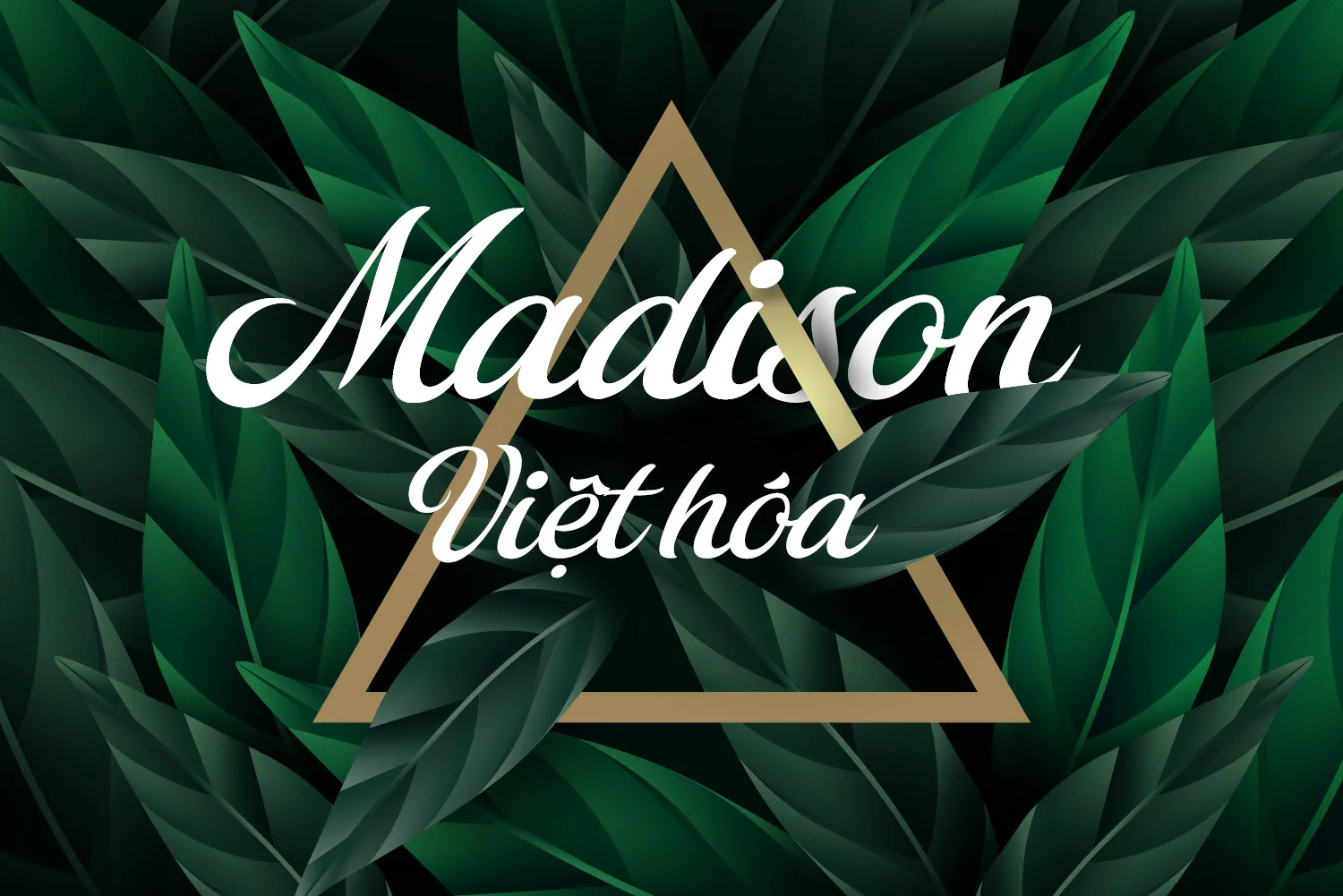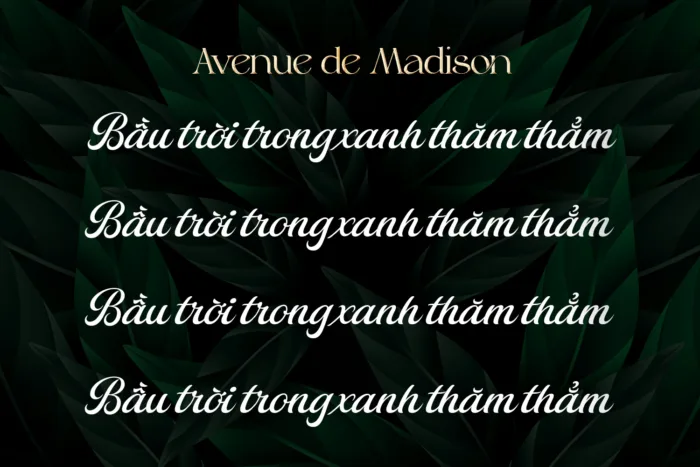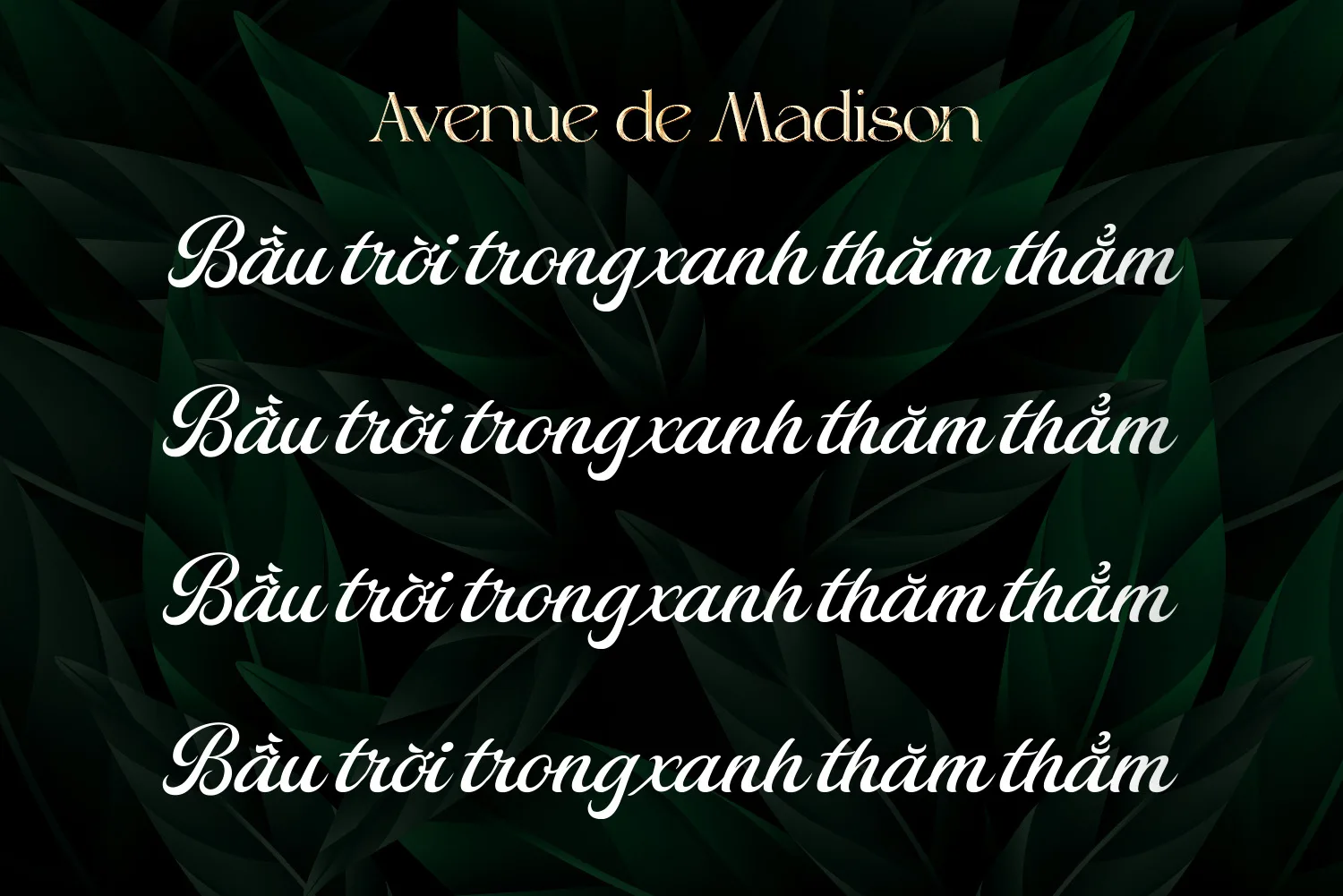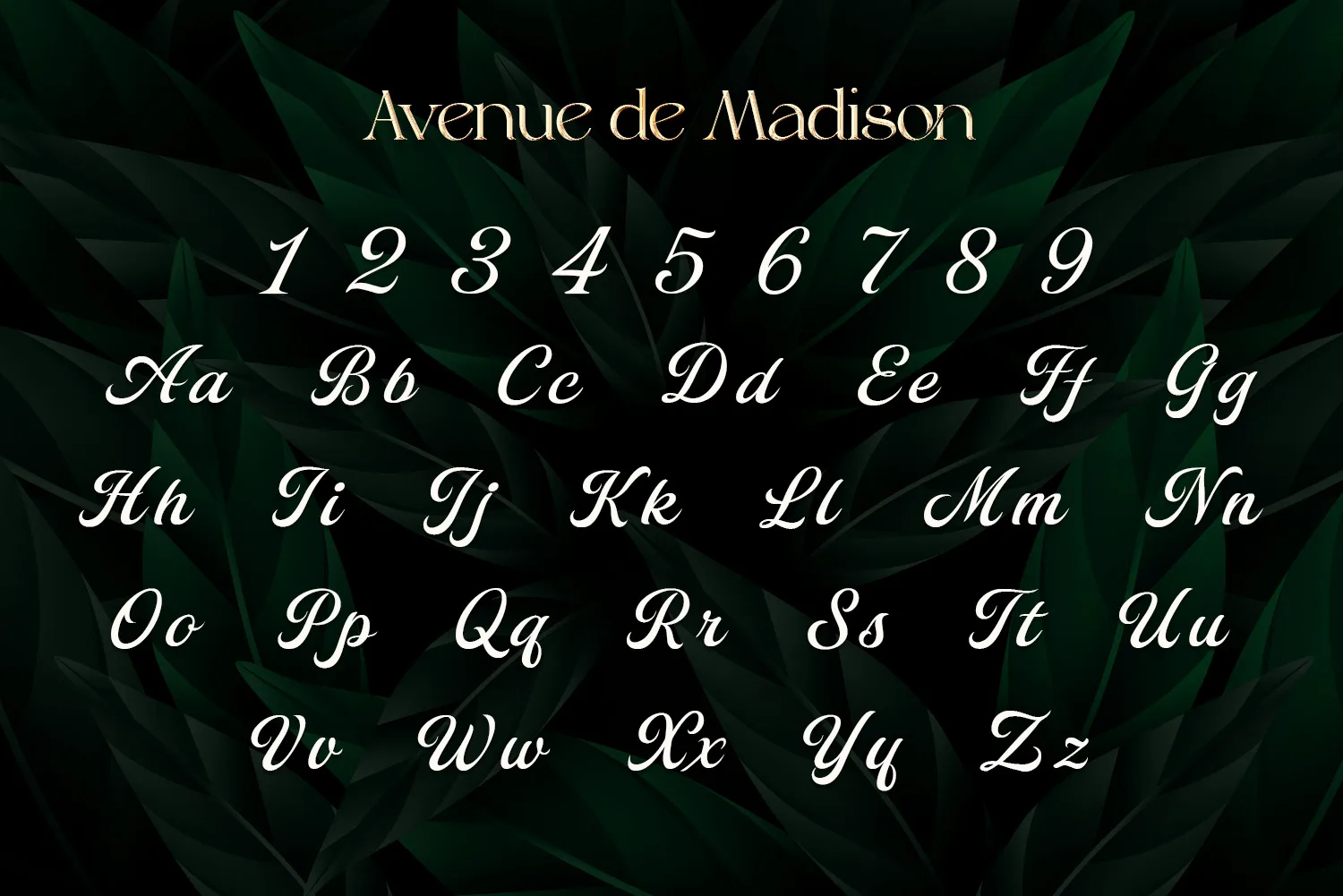
DVN Avenue de Madison Việt hóa – Font chữ Viết tay thanh lịch, mềm mại cuốn hút
DVN Avenue de Madison Việt hóa là một font chữ script mang phong cách viết tay nhẹ nhàng, tinh tế và duyên dáng. Với các nét chữ uyển chuyển, mềm mại nhưng vẫn giữ được sự rõ ràng và cân đối, font này đặc biệt phù hợp cho các thiết kế thiệp mời, logo thương hiệu, tiêu đề tạp chí, ấn phẩm thời trang, hay bất kỳ dự án nào cần sự sang trọng và nữ tính. Bộ chữ cái hoa được trau chuốt cầu kỳ, tạo điểm nhấn nổi bật, trong khi chữ thường giữ nhịp điệu mượt mà và hài hòa. Phiên bản Việt hóa hỗ trợ đầy đủ dấu tiếng Việt, đảm bảo trải nghiệm trọn vẹn và tiện lợi cho người dùng sáng tạo nội dung tiếng Việt. Đây là sự lựa chọn hoàn hảo cho những ai đang tìm kiếm một font chữ viết tay mang tính nghệ thuật cao mà vẫn dễ ứng dụng.